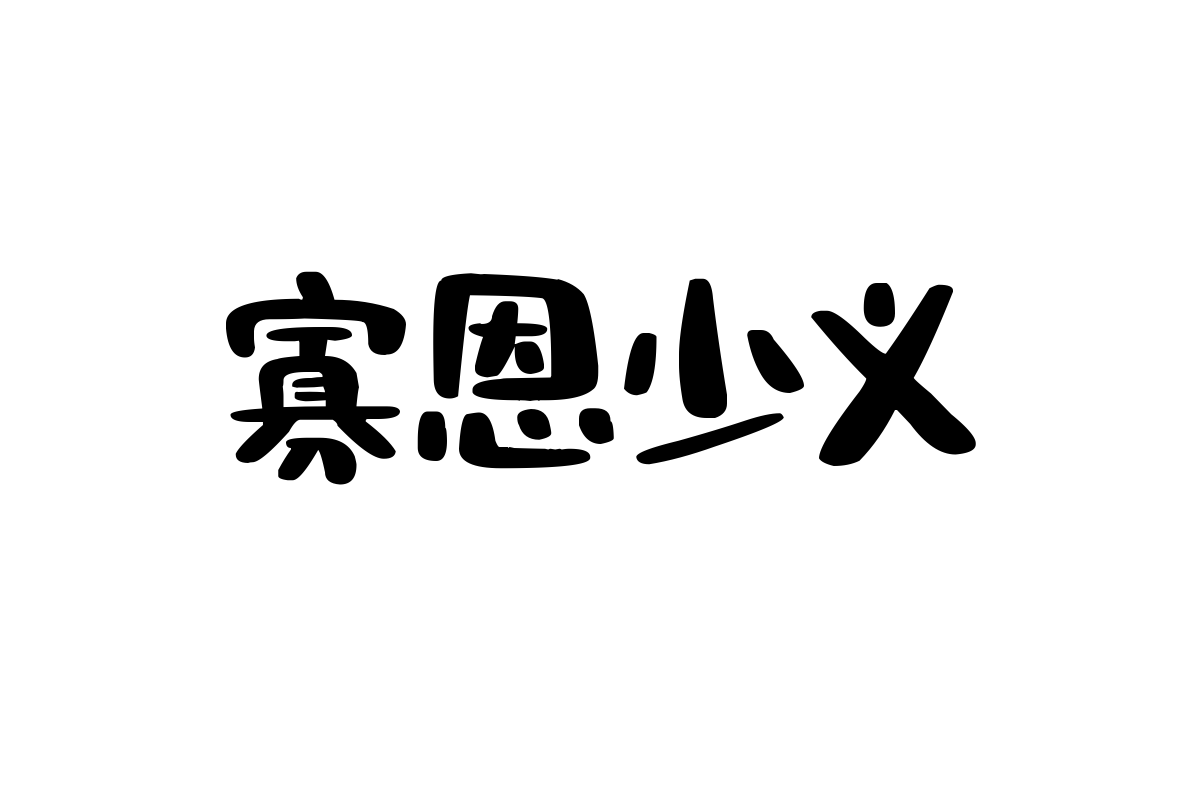
造字工房妙意体是一套由造字工房设计的字体,旨在通过创新的设计和独特的字形,为文字带来新的视觉体验。这款字体以其独特的风格和创意,吸引了众多设计师和艺术家的喜爱。
在设计上,造字工房妙意体注重细节和个性,通过巧妙的笔画组合和形状变化,创造出独特的视觉效果。这种设计不仅让文字更加生动有趣,还能提升整体的美感和艺术感。
此外,造字工房妙意体还具有很高的可读性和实用性。无论是在网页设计、海报制作还是其他平面设计领域,这款字体都能展现出其独特的魅力。同时,它的适用范围也非常广泛,可以用于各种类型的文本内容,满足不同场景的需求。
总的来说,造字工房妙意体是一款极具创意和个性的字体,它不仅能为文字带来全新的视觉体验,还能提升整体的设计效果。无论是个人使用还是商业用途,都值得一试。